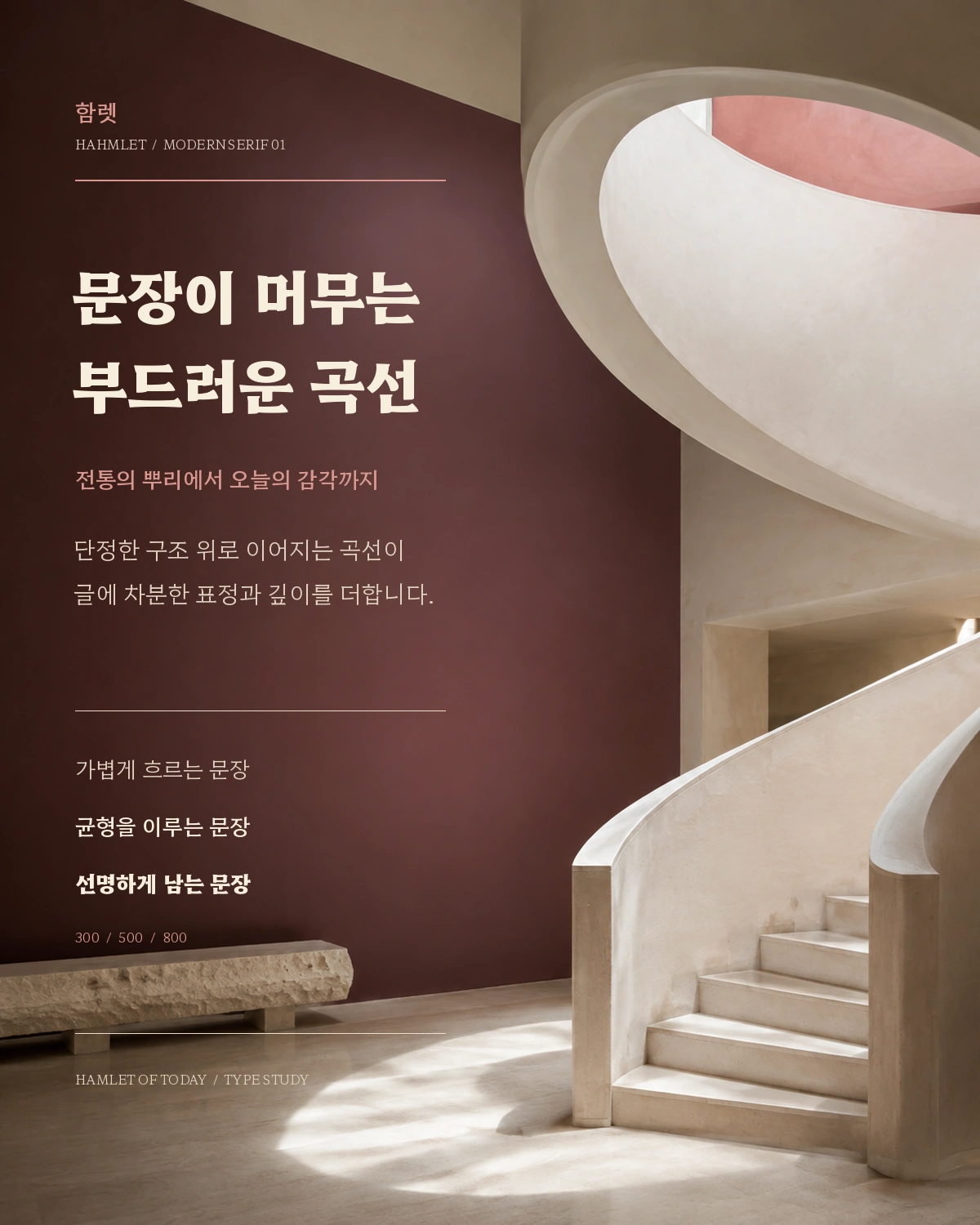
함렛 — Hypertype에서 배포하는 무료 폰트입니다. 1940년대 영화 포스터의 제목 글자를 복원해 현대적으로 다듬은, 날카로운 인상의 명조 계열 서체
이 서체의 출발점은 1940년대 한국 영화 「햄릿」 포스터의 제목 글자입니다. 이름 모를 간판 글씨쟁이가 그린 그 글자의 독특하고 날카로운, 어딘가 별난 디테일이 눈에 띄어 함민주가 흔치 않은 복원 프로젝트로 삼아 현대적인 서체로 다듬었습니다. 한글이 완성된 뒤에는 마르크 프룀베르크가 그 특징을 라틴 문자로 옮기는 작업을 맡았습니다. 두 사람이 함께 운영하는 다국문자 서체 스튜디오가 하이퍼타입입니다.
이름 함렛은 그 영화 제목에서 왔습니다. 제작자는 이 서체가 인쇄든 화면이든 어떤 조판에도 잘 맞고 사이니지와 포스터에서는 시선을 끄는 역할도 한다고 밝히면서, 한글과 라틴이 완벽하게 어울리도록 설계했다고 적었습니다.
굵기는 Thin부터 Black까지 아홉 단계이고 가변 폰트로도 나옵니다. 구글폰트 라이브러리에서 한글을 지원하는 첫 가변 폰트로 알려져 있습니다. 오픈 폰트 라이선스로 배포되어 수정과 재배포가 자유롭고 221개 언어를 지원합니다. 다만 한글은 2,788자로 완성형 전체는 아닙니다.